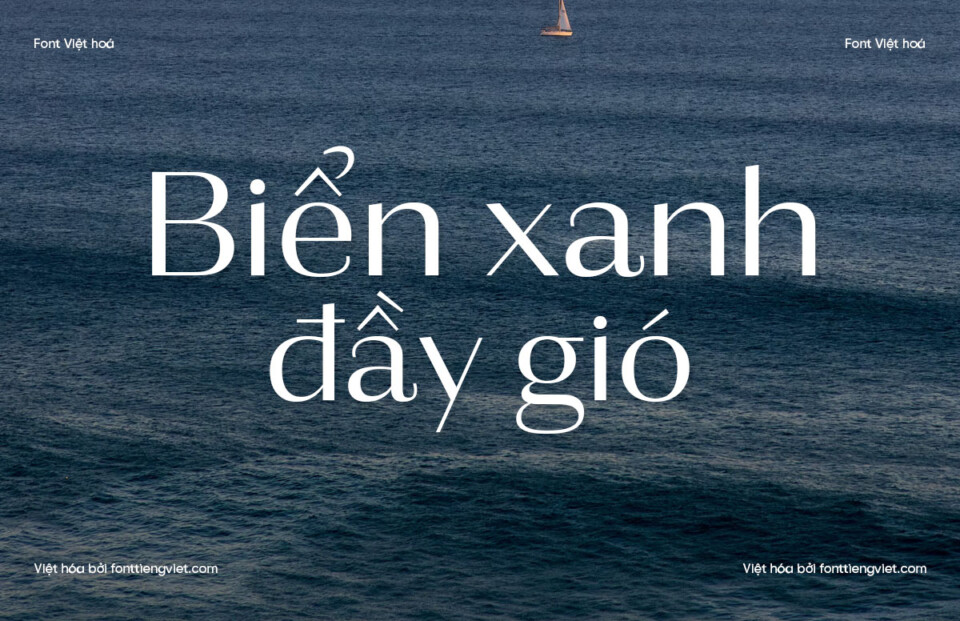
Font Việt hóa 1FTV VIP Valter Std – Lựa Chọn Hoàn Hảo Cho Thiết Kế Học ĐườngGiới thiệu về Font Việt hóa 1FTV VIP Valter StdTrong các hoạt động giáo dục, việc lựa chọn một Font Miễn Phí và rõ chữ luôn là ưu tiên hàng đầu của thầy cô và các em học sinh. Bộ Font Việt hóa 1FTV VIP Valter Std chính là một giải pháp thiết kế tuyệt vời như thế. Với các đường nét thanh lịch, rõ ràng và hiện đại, bộ font này giúp mọi văn bản trở nên dễ đọc và thu hút hơn. Phiên bản Việt hóa hoàn chỉnh giúp người dùng hoàn toàn yên tâm, không còn lo lắng về lỗi font khi gõ tiếng Việt có dấu.Ưu điểm nổi bật của Font Việt hóa 1FTV VIP Valter Std trong học tậpThiết kế bài giảng sinh độngBộ Font Việt hóa 1FTV VIP Valter Std sở hữu cấu trúc các ký tự rất cân đối, mang lại cảm giác dễ chịu cho mắt người nhìn. Khi thầy cô ứng dụng bộ chữ này vào các slide bài giảng điện tử, học sinh sẽ dễ dàng tiếp thu kiến thức một cách tập trung hơn. Độ dày của các nét chữ được tinh chỉnh hoàn hảo, giúp hiển thị sắc nét trên cả màn hình máy tính lẫn máy chiếu lớp học.Ứng dụng làm báo tường và tài liệuKhông chỉ dùng cho bài giảng, tựa game hay đồ họa lớp học, phong cách của font chữ này còn rất hợp để làm tiêu đề báo tường, làm thiệp chúc mừng hoặc thiết kế các tài liệu học tập nội bộ. Sự linh hoạt của nó giúp các bạn học sinh thỏa sức sáng tạo các sản phẩm truyền thông của trường lớp.Kết luận và cách tải font chữ chuẩnViệc sở hữu một bộ chữ đẹp và đa năng sẽ giúp nâng cao chất lượng thẩm mỹ cho mọi sản phẩm học đường. Hãy truy cập ngay kho dữ liệu Font Miễn Phí, Font Việt Hóa, Font Việt hóa 1FTV VIP Valter Std để tải về và trải nghiệm thiết kế. Chúc các bạn và thầy cô có những tác phẩm sáng tạo xuất sắc nhất.
Font Việt hóa 1FTV VIP Valter Std